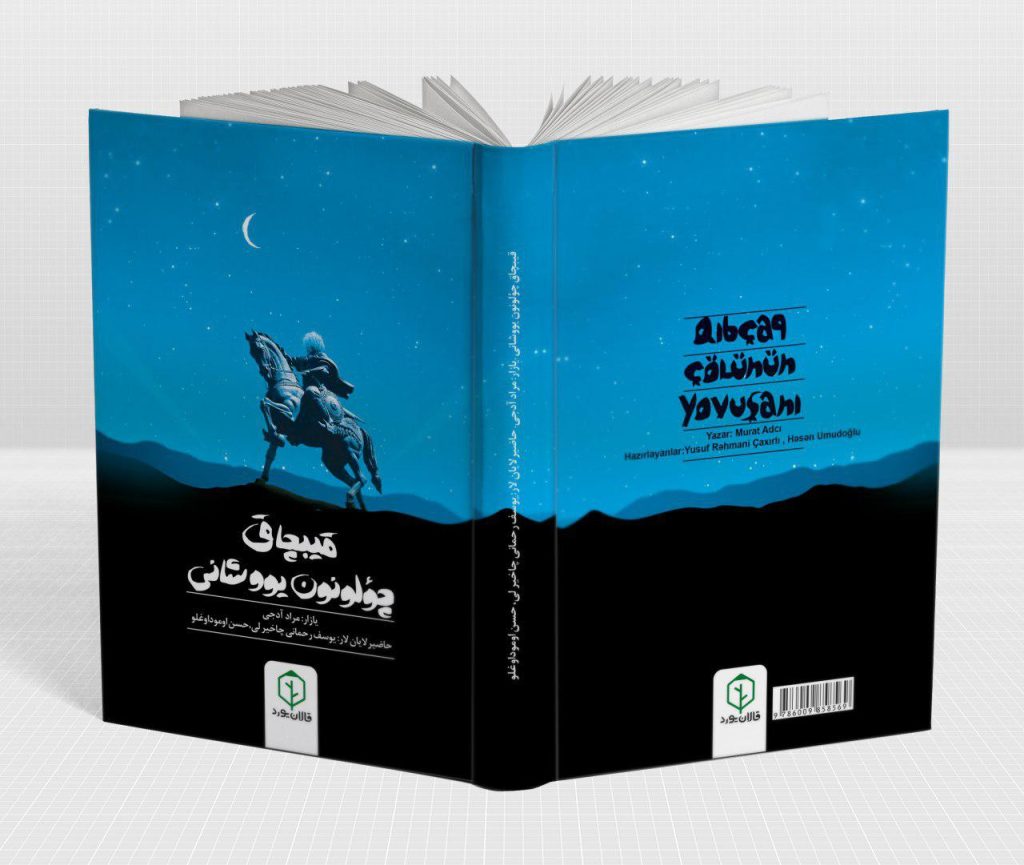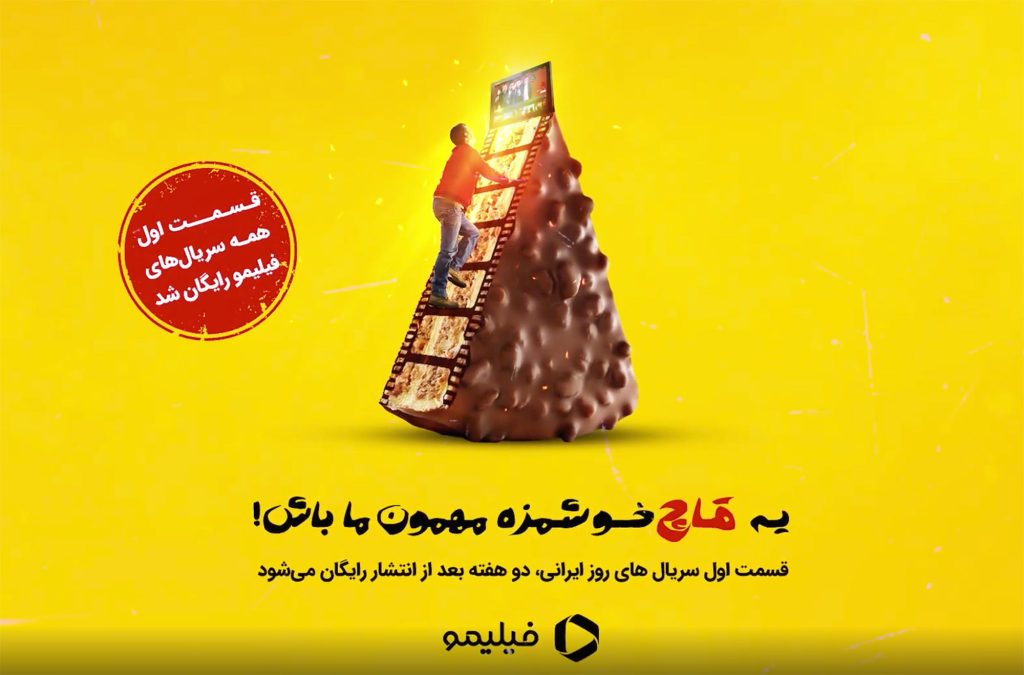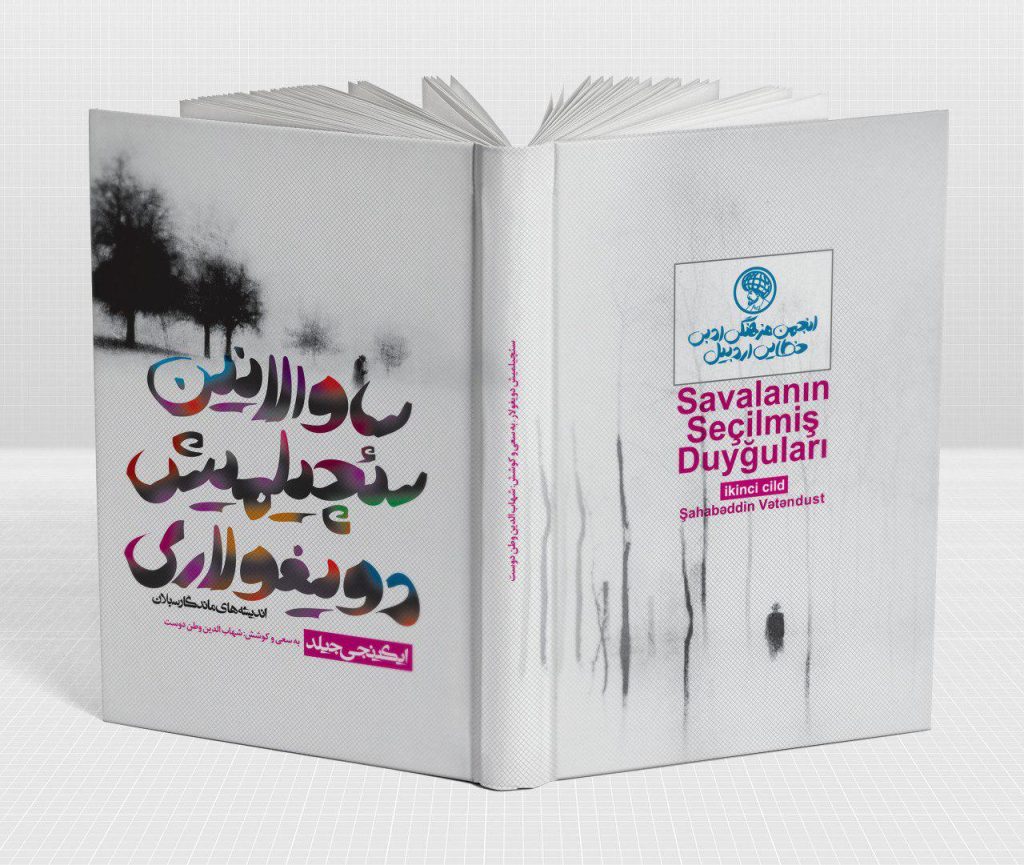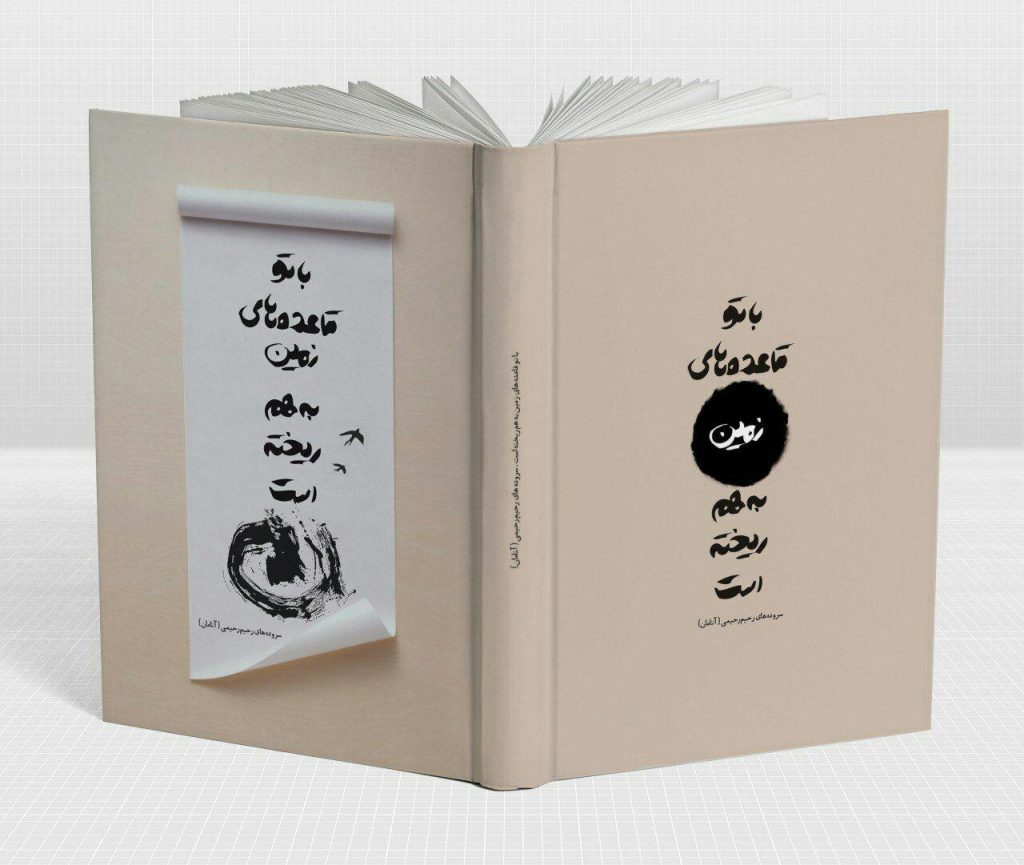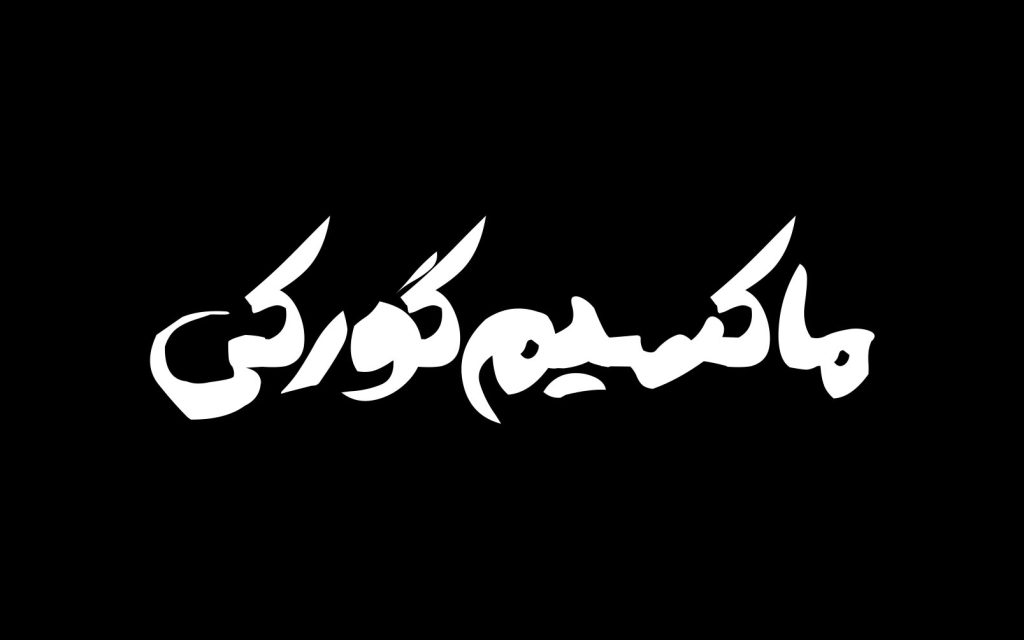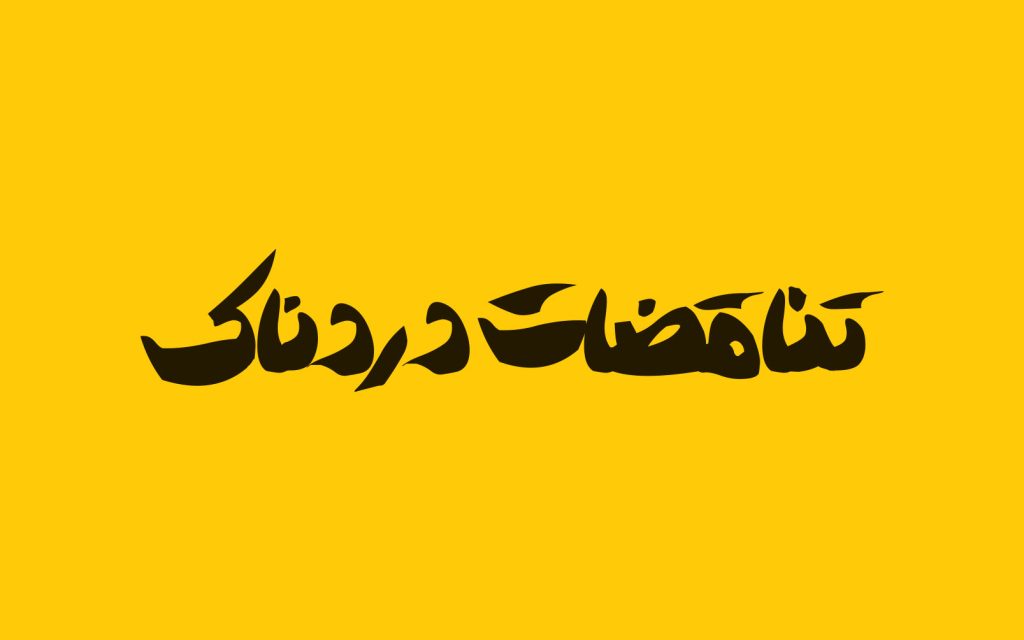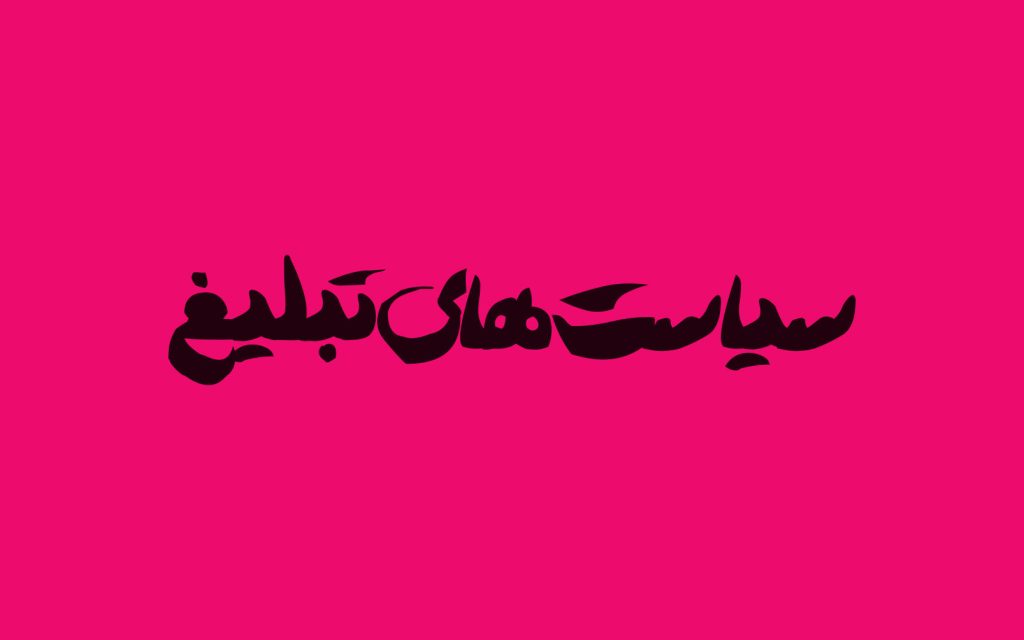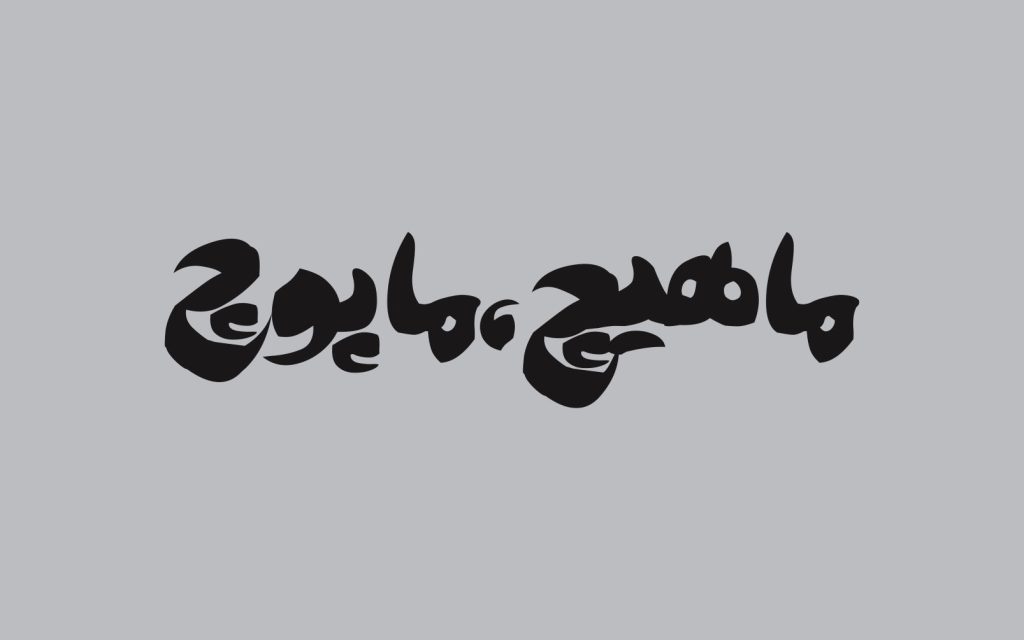
فونت آتابای
فونت اتابای تایپ فیسی از خانواده دست نویس با ظاهر و طراحی خاص فرم های حروف و گلیف های آن بی شک قلمی منحصر به فرد و خاص به شمار می رود. رهایی و آزادی عمل زیاد و بی قید و شرط بودن از ویژگی های این قلم است. و پایبندی محکم به نظم و نظام مرسوم در قلم های فارسی در این قلم مشاهده نمی گردد. و دارای تیپ و شخصیتی غیرماشینی و بسیار خاص و منحصر بفرد دارد .
پر واضح است که این قلم مناسب برای متون کوتاه و عناوین و تیتر ها از دنیای دیجیتال تا صنعت نشر و چاپ است. روحیه پرانرژی و فعال و در عین حال به روز و جوان دارد و از فضای رسانه امروزی نه تنها جدا نیست بلکه نزدیک و هماهنگ با آن است. می توانید پس از دانلود این تایپ فیس آن را در پست های مقاله های اینستاگرام و مقاله های دنیای وب نیز استفاده کنید.
قدرت نمایشی و جاذبه اتابای
مهم ترین ویژگی آتابای نمایشی بودن آن است . اساسا طراحی شده تا جاذب نگاه باشد. از این نقطه نظر می توان به فونت پتک اشاره کرد که با ظاهر خاص و طراحی فرم حروف خود از دسته قلم های خاص با ویژگی نمایشی بالا می باشد.
طراح این قلم هادی ارجمند با قصد ساخت و طراحی یک قلم شخصی، آتابای را طراحی کرده تا بتواند به کمک آن طرحهای گرافیکی خویش را منحصر به فرد نمایش دهد. فیالبداهگی و تحرک بسیار زیاد و آزادگی در عمل این تایپ فیس ویژگی خاص و منحصر به فرد این قلم داده است.
حروف در این تایپ بصورت تک تک نگارش شدهاند و سپس در اجرای نرم افزاری اتصالهای تک تک گلیف ها ایجاد گردیده است. این فونت جهت عناوین کوتاه و تیتر های تبلیغاتی انتخابی بسیار مطمئن می باشد.
در این قلم تنظیمات اعراب وجود دارد اما از زبان عربی بصورت کامل پشتیبانی نمیکند.
این تایپ فیس فاقد حروف و اعداد انگلیسی است. (اعداد کاملا فارسی است)